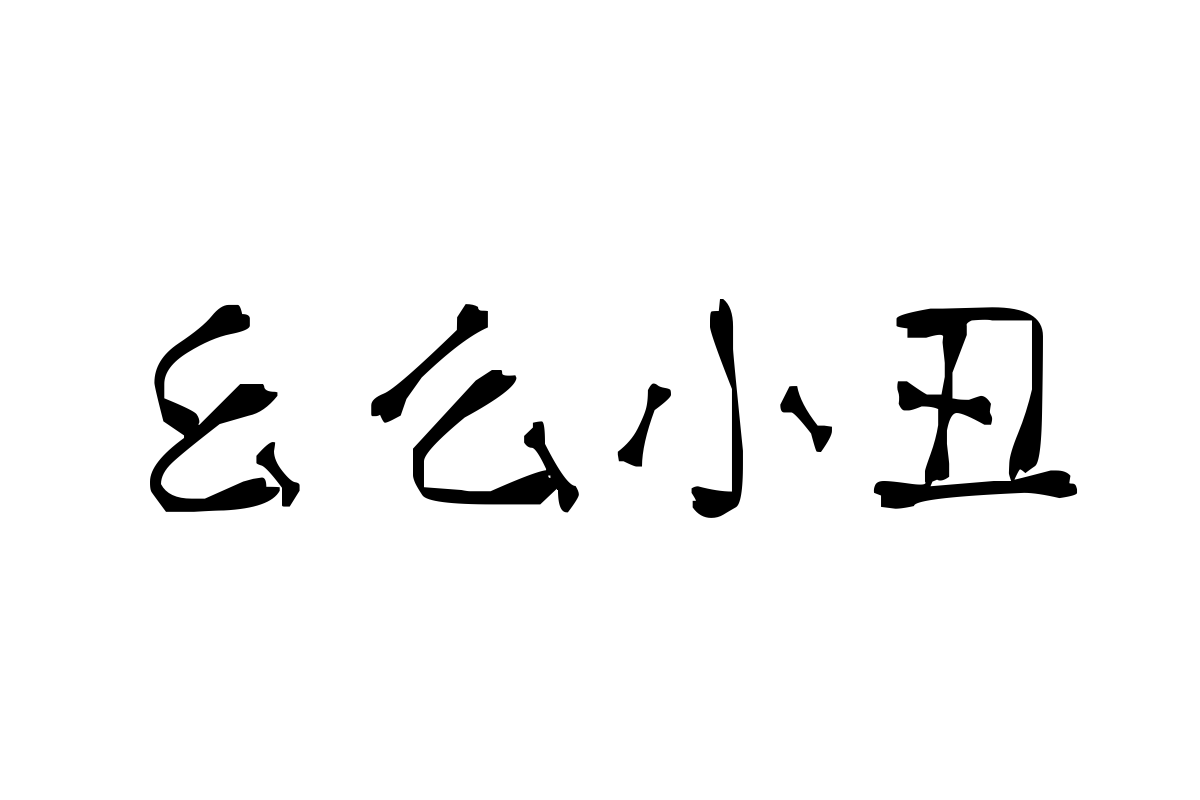
汉标馋骨体是一套具有现代感和艺术感的中文字体,由汉标字库设计。这款字体以其独特的字形结构和笔画风格,给人以强烈的视觉冲击力。
该字体的特点如下:
1. 字形结构独特:汉标馋骨体的字形结构独特,笔画流畅,线条粗细变化丰富,给人一种强烈的视觉冲击力。
2. 笔画风格鲜明:汉标馋骨体的笔画风格鲜明,线条粗细变化丰富,给人一种强烈的视觉冲击力。同时,该字体的笔画也具有一定的艺术感,使得整体视觉效果更加美观。
3. 适用范围广泛:汉标馋骨体适用于各种应用场景,如广告、设计、印刷等。其独特的字形结构和笔画风格,使得它在众多字体中脱颖而出,具有较高的辨识度。
总之,汉标馋骨体是一款具有现代感和艺术感的中文字体,其独特的字形结构和笔画风格,使得它在众多字体中脱颖而出,具有较高的辨识度。同时,它的适用范围广泛,易于使用,为设计师们提供了更多的选择。